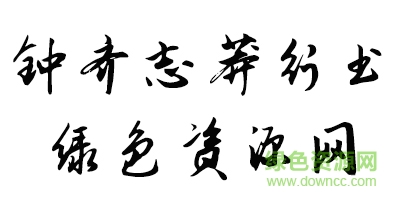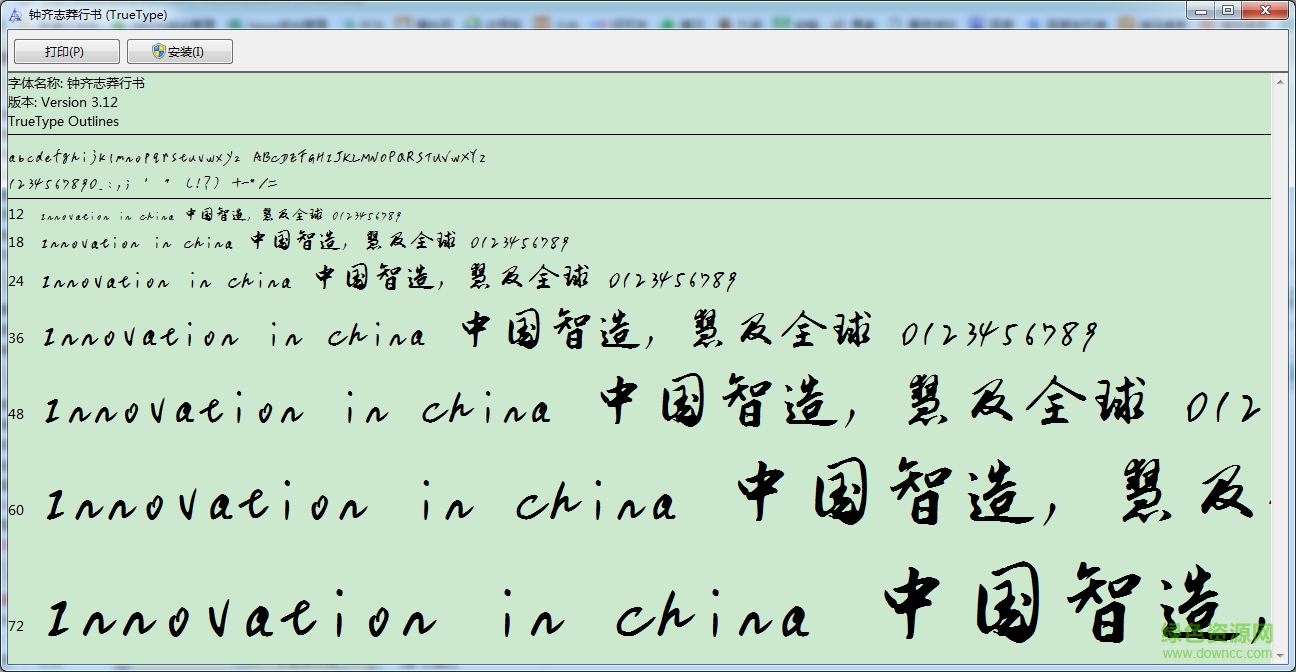
鐘齊志莽行書字體是一款非常有藝術特色的書法字體,這款字體字形瀟灑飄逸,形體端秀而骨架勁挺,整體效果非常出色,非常適用于廣告設計、藝術設計、書法練習等,喜歡這款字體的朋友歡迎來綠色資源網(wǎng)下載體驗!
鐘齊志莽行書是由上海鐘齊字庫公司根據(jù)書法家韋志莽先生毛筆書法字庫開發(fā)而成的一款中文行書書法字體。鐘齊志莽行書字體廣泛適用于廣告設計、包裝設計等方面。